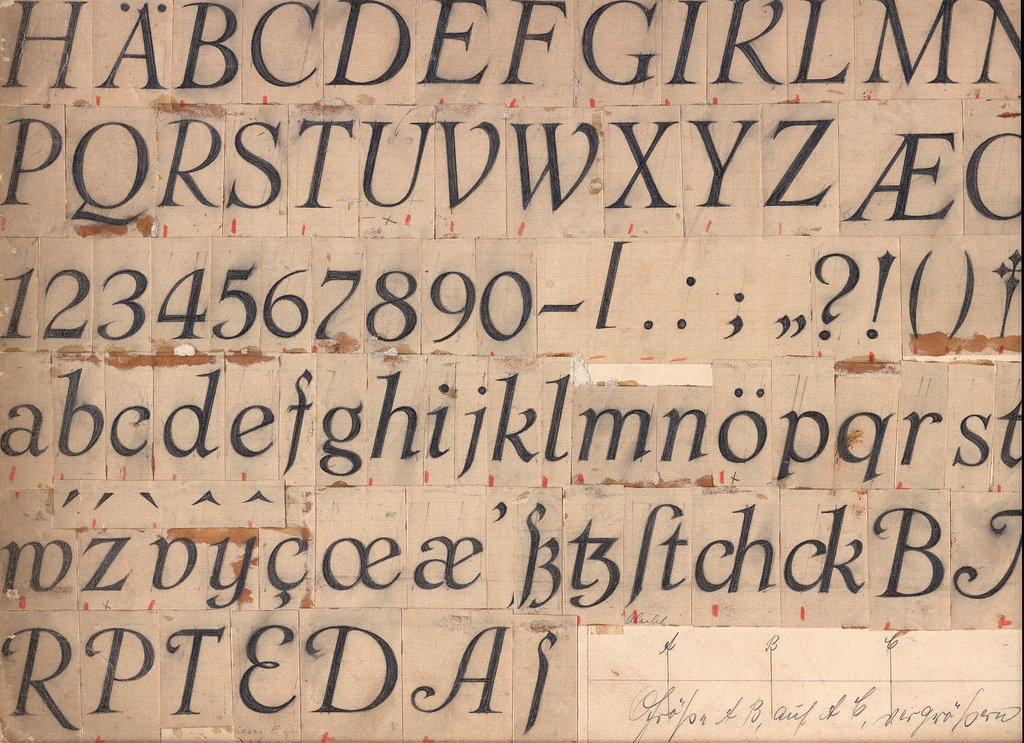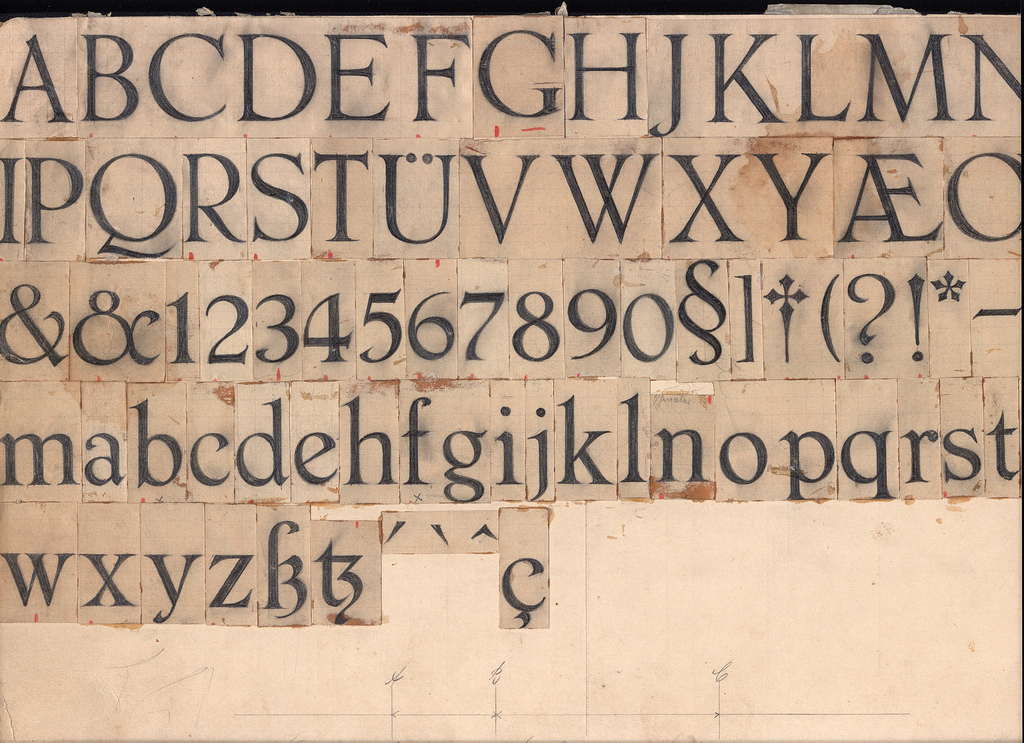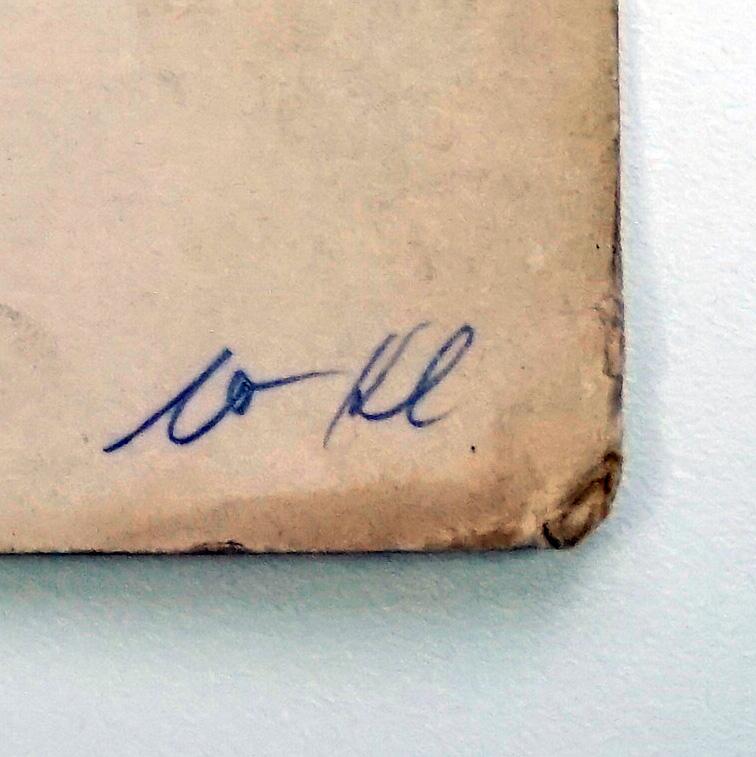
Schriftskizzen-Fundstück
Hat jemand eine Ahnung welche Schrift das sein kann? Die beiden Muster sind mit Bleistift gezeichnet und gestückelt auf Pappen aus der Schriftgießerei Trennert aufgeklebt. Die Skizzen sind schätzungsweise aus den frühen 30er Jahren, denn die Rückseite zeigt die Fette Trennert-Fraktur von 1931.
wie gesagt, lag bei einigen schriftproben aus der schriftgießerei trennert dabei und ist auf karton geklebt welcher auf der rückseite auch mit j. d. trennert beschriftet ist.
Ja, vermute ich auch, umso spannender ist das Thema.
Das was ich von Trennert habe, habe ich durchgesehen. Den Seemann auch grob, wobei ich ausschließen würde das die Schrift dort drin ist, weil dieser von 1926 ist und die Rückseite des Kartons die Trennert-Fraktur von 1931 zeigt.
ich vermute das es was von Kleukens ist, es passt zu seinem Stil und die Trennert-Fraktur ist auch von Ihm.
Außerdem befindet sich auf dem einen Muster unten rechts ein Kürzel was man als Kl. deuten könnte.
Ich hab mir das auch noch mal genauer angeschaut, und auch den ganzen Seemann durchgesehen.
Schaut wirklich nach etwas unveröffentlichtes und wirklich sehr nach Kleukens' Handschrift aus, sodass man die wohl Kleukens Mediäval nennen könnte, oder?
Florian unterstreicht meine These mit Kleukens:
Interesting question! I don’t know the answer, but here are some observations.
Several of the peculiar letterforms remind me of details in typeface designs by Friedrich Wilhelm Kleukens. For example, the ‘e’ is almost exactly the same as in Kleukens-Antiqua. Compare also the unusual construction of ‘Q’, the ‘tz’ ligature with the descending terminal, the curling question mark, or the pointy exclamation mark. Furthermore, have a look at Neue (Kleukens) Antiqua, an unrealized design made in 1928 (shown in Klingspor-Museum’s pdf). In particular, see the ‘R’ with the large head and the flowing leg, the left-leaning ‘Æ’, the ‘&’ with the left-pointing arm, the curved ‘7’ and, most strikingly, the distinctive ‘4’. The ‘a’ with the round belly can be found (in a different form) in his Ratio-Latein. Some of this´could be ascribed to the fashion of the time, but in sum, I find it suspicious. Could this be a design by Kleukens himself, or a pupil or epigone of his?
F. W. Kleukens released most of his designs with Bauer (Kleukens-Antiqua, 1910–13) and Stempel (several, 1910–26). At the end of his career, however, he made Ferrum (1930) and Trennert-Fraktur (1931) for J. D. Trennert. The latter was started at Stempel, where a trial cut was made in 1927 as Kleukens-Fraktur. It is unclear why Stempel didn’t go forward with the production, and why Trennert took over. [W. Hendlmeier]
Trennert-Fraktur was also adopted for the Typograph machine, in three weights, with duplexed matrices. It features a very similar ‘4’, too.
Could it be that your images show the drawings for a revised version of a Neue Kleukens-Antiqua, to be produced for Trennert/Typograph, after Kleukens and Stempel parted ways?
Genau diese beschriebenen Formprinzipien habe ich bei meiner Betrachtung diverser Kleukens-Schriften auch gesehen. Besonders dieses besondere Q war mir fast schon der Aufhänger, eine ähnliche Schrift zu finden, und dann wear das sicher ne Kleukens-Schrift und auch einige der Formprinzipien fanden sich dann wieder.